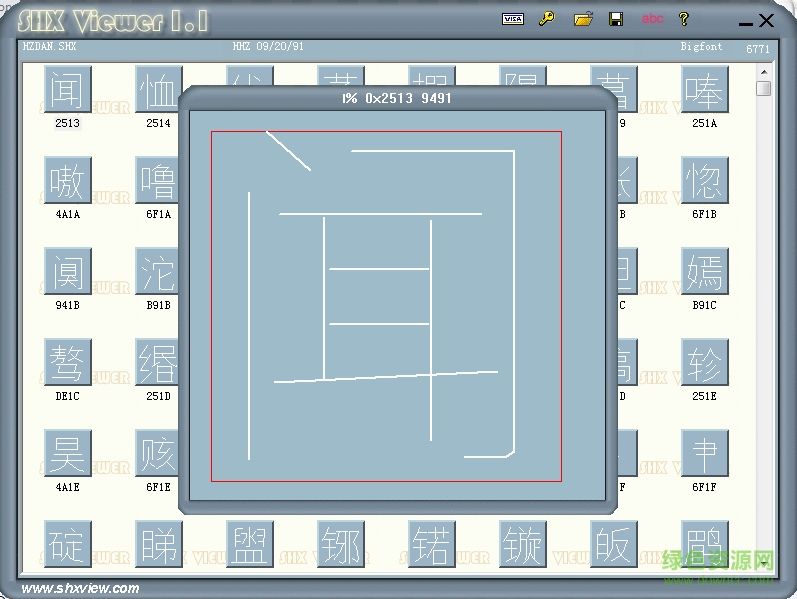
hzdan.shx是一款擁有6771個字的cad字體,歸屬于大字體系列,支持部分繁體字輸入,字跡精簡如鐫刻,給人純凈清秀的閱讀觀感,綠色資源網(wǎng)誠意推薦!
1、在dwg文件的存儲上占用的空間小,在顯示的速度上比較快。特別是文字比較多的情況下,regen的重顯的速度上的差異更明顯,在實(shí)時移動(pan)的更新上不存在時差現(xiàn)象。
2、由于windows字體為外來字體(相對于shx字體),在生成及編輯的過程中,還不能做到完美無缺。比如,truetype字體(windows字體)的文字在移動、拷貝的過程中,句子的長度可能與實(shí)際的長度不同,影響了參考定位。再如,truetype字體的實(shí)際高度可能與指定的高度之間有差異,不能精確地指定字高,只能通過試錯的方式確定,影響了繪圖的速度,也影響了編程控制的難度。 3、由于shx字體為線型字體,可以像線段一樣指定特別屬性,產(chǎn)生特殊效果。比如,可以指定厚度值,從而產(chǎn)生立體效果。
4、與truetype字體相比,shx字體美觀效果不夠理想,但在工程中尚可滿足需要。shx字體相當(dāng)于硬筆書法,在模擬毛筆書法上存有差距。